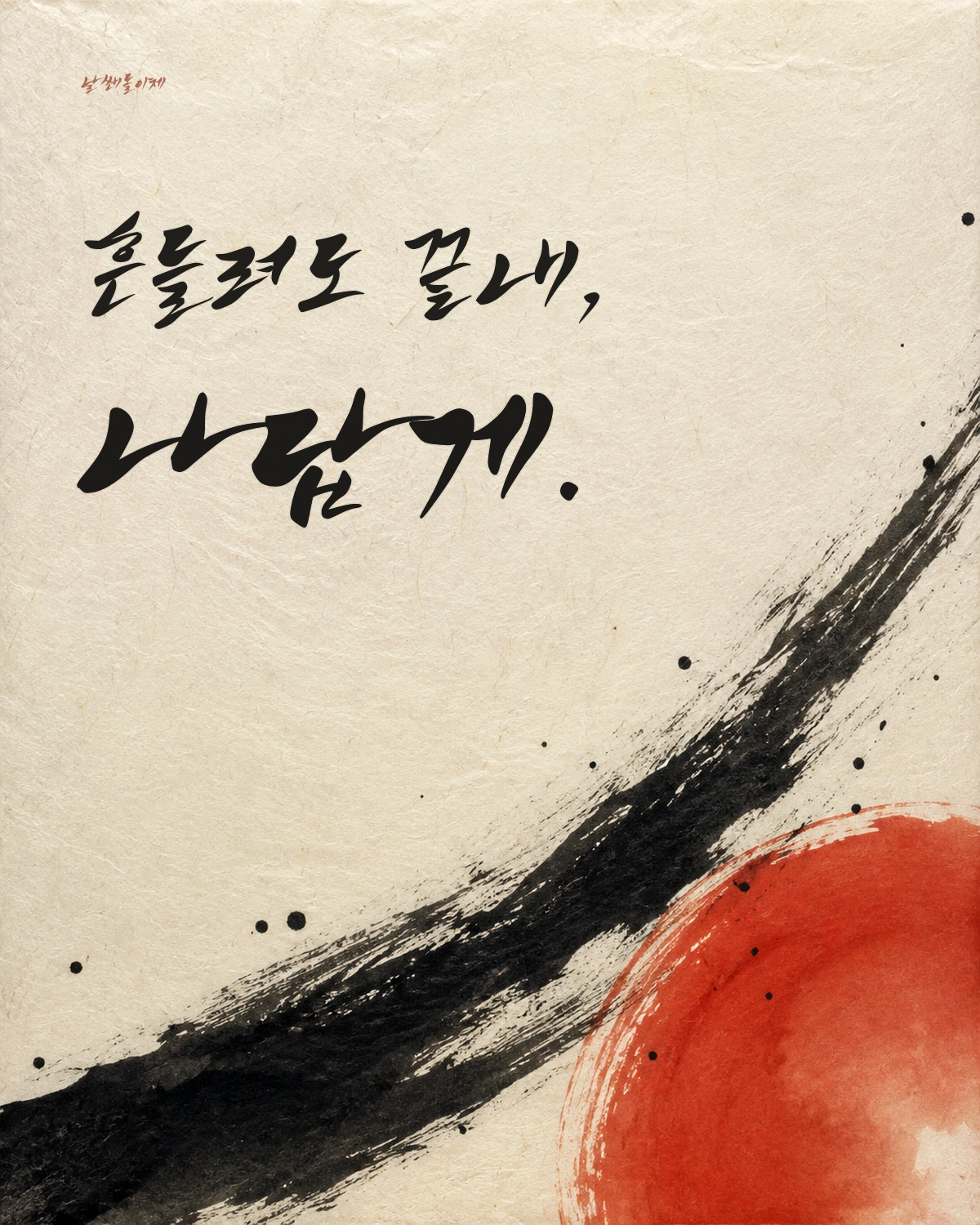
날쌘돌이체 — 캘리폰트에서 배포하는 무료 폰트입니다. 리듬감이 살아있는 경쾌한 스타일의 캘리그라피 서체
같은 캘리폰트에서 나온 서체로 이름 그대로 빠르게 쓴 붓펜 필기체입니다. 쿨가이체와 마찬가지로 제작자 정보나 제작 배경은 공개돼 있지 않고 사이트 소개 문구도 공용 문장이라, 형태는 파일을 직접 보고 적었습니다.
획이 빠르게 지나간 자리에 갈필 자국이 남고 획 끝이 가늘게 빠지는 것이 특징입니다. 같은 곳에서 나온 쿨가이체가 굵기 변화 없이 일정하게 흐른다면 이쪽은 속도와 필압이 그대로 드러나 훨씬 거칠고 역동적입니다. 두 서체를 나란히 놓고 고르면 성격 차이가 분명합니다.